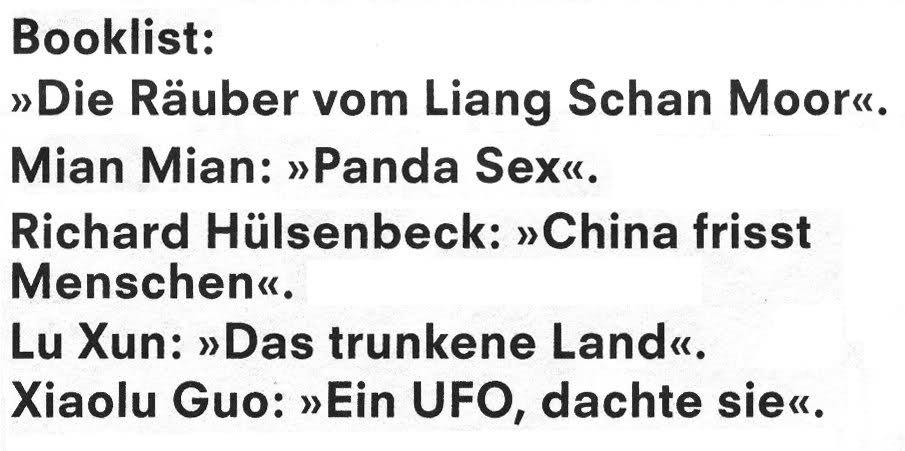
welche schrift ist das # 2
und kennt ihr die da?
Jene ist ähnlich …
Die Originalschrift ist die Neuzeit Grotesk S Heavy. Das S steht für Siemens, denn sie wurde 1965 bei der D. Stempel AG als Bleisatzschrift für Siemens entwickelt, aber auch allgemein verkauft.
ich denke, dass es sich bei meinem schriftmuster um die neuzeit grotesk s heavy handelt. deine geschichte vom original ist sehr interessant. wie bist du drauf gestossen?
Ich war zu dieser Zeit als Schriftsetzer in der Hausdruckerei der D. Stempel AG tätig.
Dort habe ich u.a. auch die Probeabzüge und Musterseiten der Schrift angefertigt.
Du hast nicht zufällig noch Schriftmuster herum liegen die du loswerden möchtest?
Von der Neuzeit S habe ich noch den Original-Proben-Abzug in 28pt Größe,
von der Neuzeit S kräftig den Abzug der Grade 16pt und 24pt.
Meine Sammlung an Schriftprobenheften und Büchern befindet sich im Gutenberg-Museum in Mainz und kann dort über die Bibliothek eingesehen werden.
Die gezeigte Schrift könnte man auch Helvetura nennen.
Oder Helvegarde :hammer: